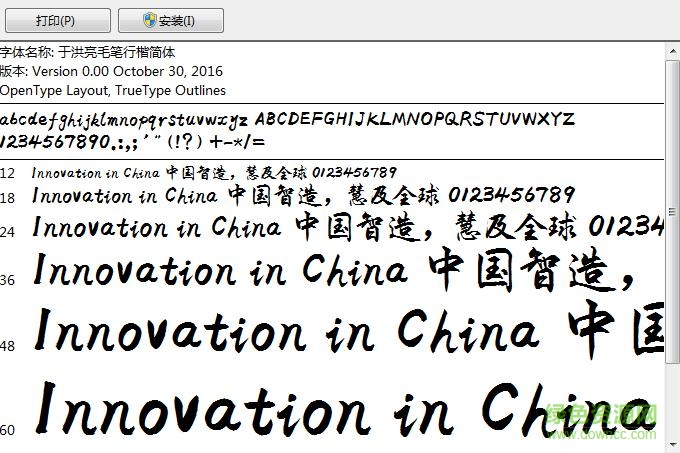
于洪亮毛筆行楷簡體
于洪亮毛筆行楷簡體是一款非常優(yōu)美的書法字體,該字體尾部的甩尾有力且有豐富的筆觸細(xì)節(jié),效果突出且引人注目,喜歡的朋友歡迎下載使用!
于洪亮毛筆行楷簡體簡介
于洪亮毛筆行楷是一款根據(jù)書法家于洪亮毛筆書法打造而來的行楷字體,該字體筆畫粗壯,并且最大程度還原作者書寫字形,細(xì)節(jié)表現(xiàn)完整,可以廣泛應(yīng)用于名片設(shè)計(jì)、新聞媒體、宣傳海報(bào)、ppt、影視制作以及內(nèi)容用字等領(lǐng)域。